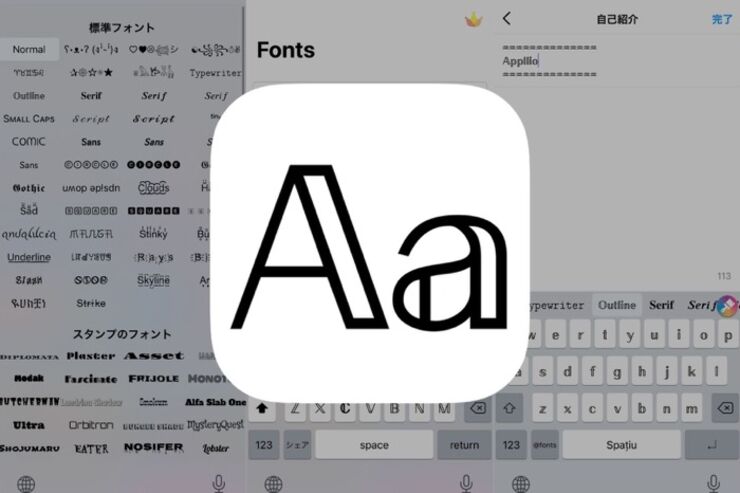
- InstagramやTwitterをオシャレに彩る特殊文字が豊富なキーボードアプリ
- コピペ不要で特殊文字を直接入力できるから入力がスムーズ
InstagramやTwitterをオシャレに彩る特殊文字が豊富なキーボードアプリ
「Fonts」は、白抜き文字や丸囲み文字といった特殊文字を入力できるキーボードアプリ。InstagramやTwitterなど、SNSのプロフィールをおしゃれに書くことができます。
普通のキーボードでは変換できないシンボルも使うことができるので、周りと差がつくSNSのプロフィールを書きたいという人におすすめのアプリです。
Fontsで使える特殊文字の一覧
Android版は完全無料で、45セットのフォントが用意されています。Fontsで使用できる特殊文字は英数字と一部の記号に対応しており、日本語入力には対応していません。
コピペ不要で特殊文字を直接入力できるから入力がスムーズ
キーボード上のフォントを左右にスワイプすると、フォントのセットを変更できます。
Instagram(左)やTwitter(右)のプロフィールや投稿に入力できる
Instagramだけでなく、Twitterでもプロフィールや投稿に特殊文字を入力することができます。特殊文字をキーボードから直接入力できるので、いろいろなフォントセットを試してみるといいでしょう。
ただし、プレーンテキストをコピペしてもFontsには反映されないので注意が必要です。